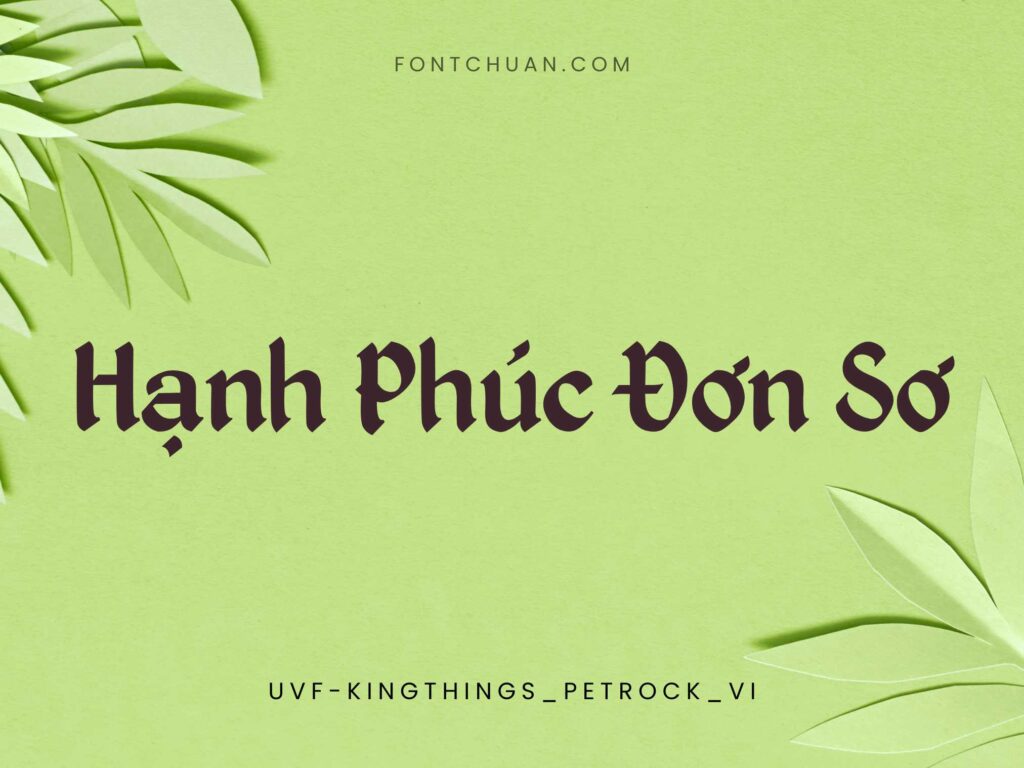
Font Kingthings Petrock Vi Việt Hóa
Kingthings Petrock là một font chữ mang phong cách cổ điển, được thiết kế bởi Kingthings. Font này lấy cảm hứng từ các chữ cái được tìm thấy trong một nhà thờ nhỏ ở Exeter, Anh Quốc, với kiểu dáng gợi nhớ đến thời kỳ Trung cổ. Với các đường nét góc cạnh và thiết kế độc đáo, Kingthings Petrock tạo nên sự khác biệt và thu hút trong các dự án thiết kế.
Font này đã được Việt hóa để hỗ trợ tiếng Việt, giúp người dùng tại Việt Nam dễ dàng sử dụng trong các dự án của mình. Kingthings Petrock phù hợp cho các thiết kế liên quan đến chủ đề cổ trang, lịch sử, hoặc các sự kiện đặc biệt như lễ hội. Ngoài ra, font này cũng thích hợp cho các ngành nghề như quảng cáo, thiết kế thiệp cưới, và các dự án nghệ thuật.